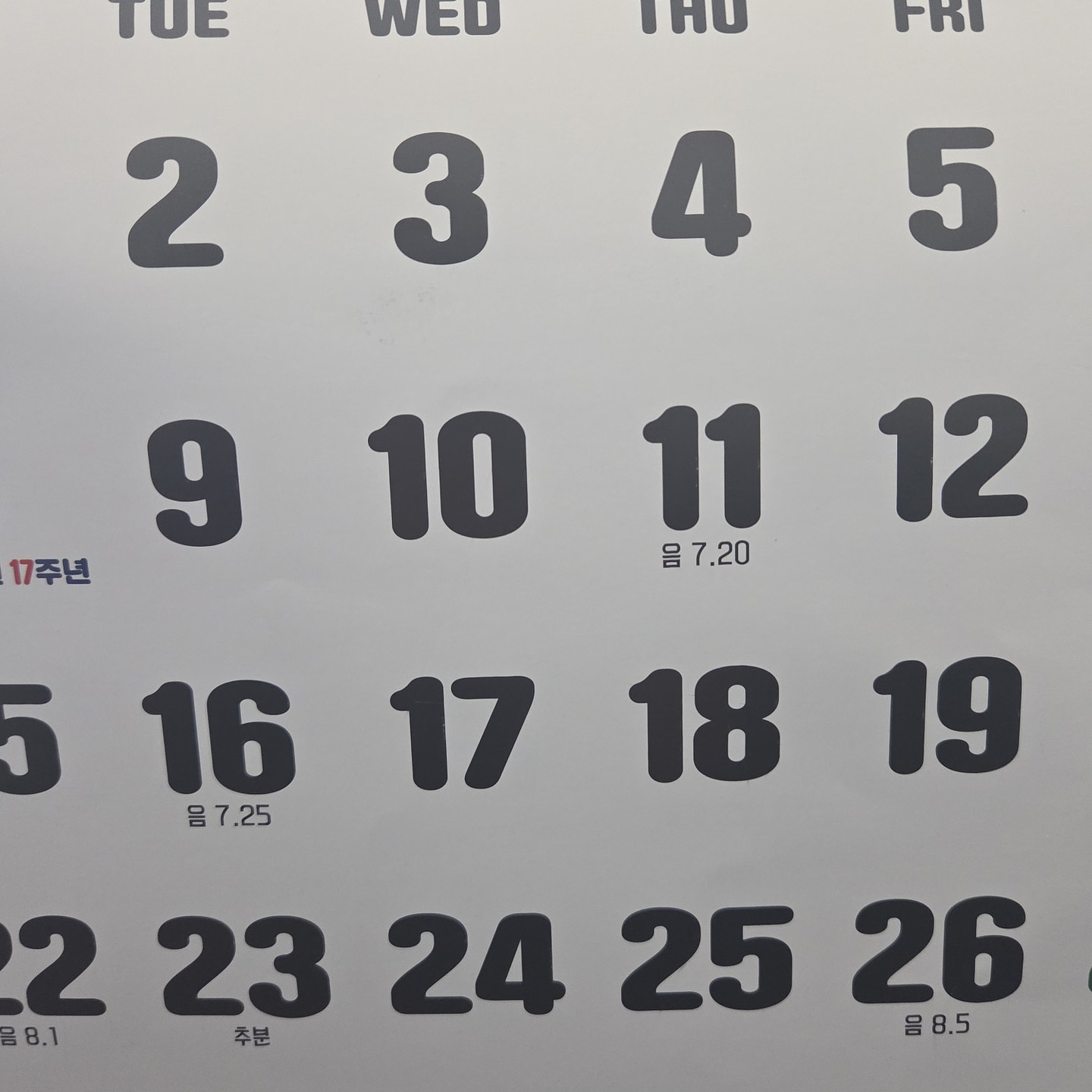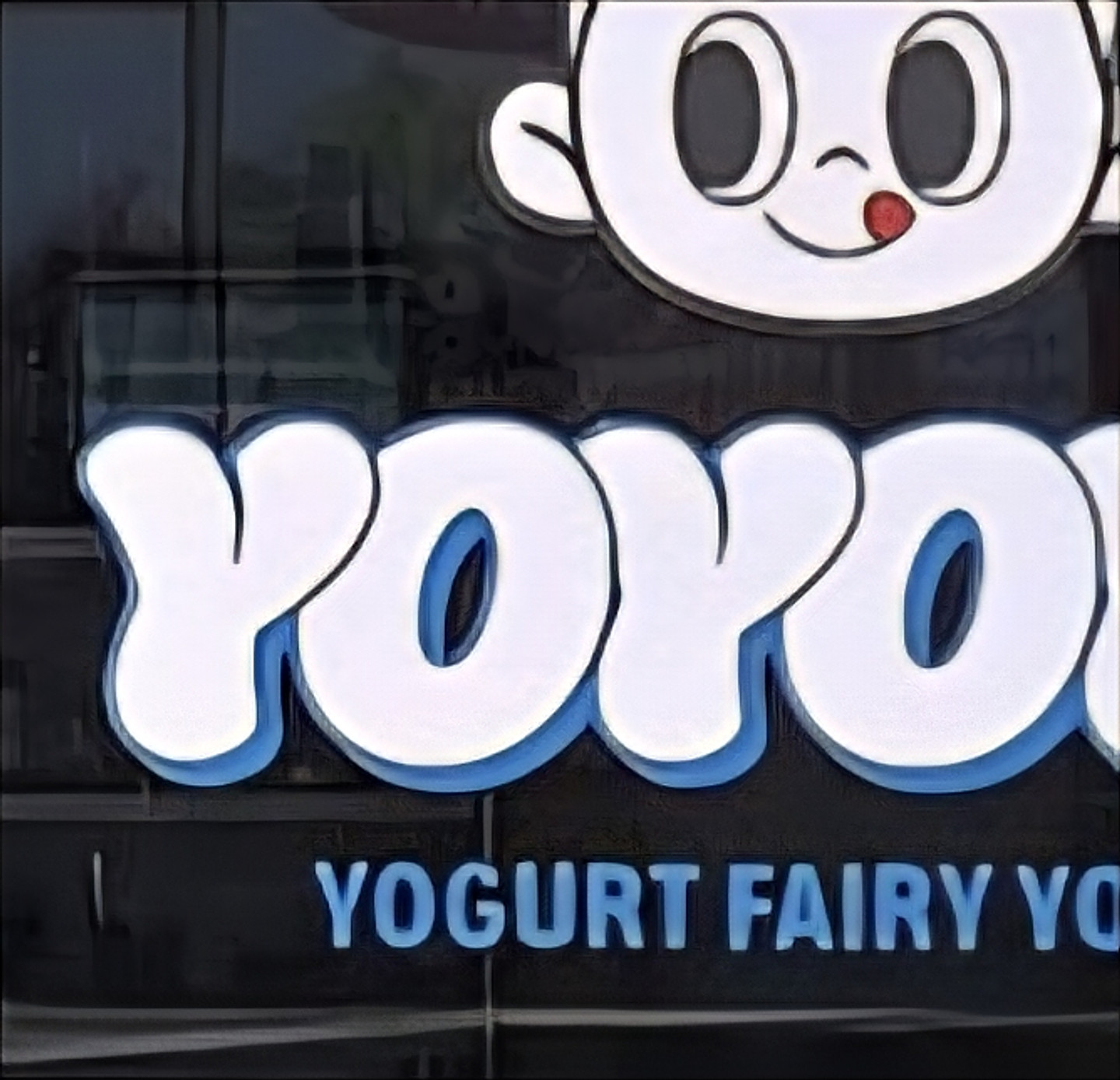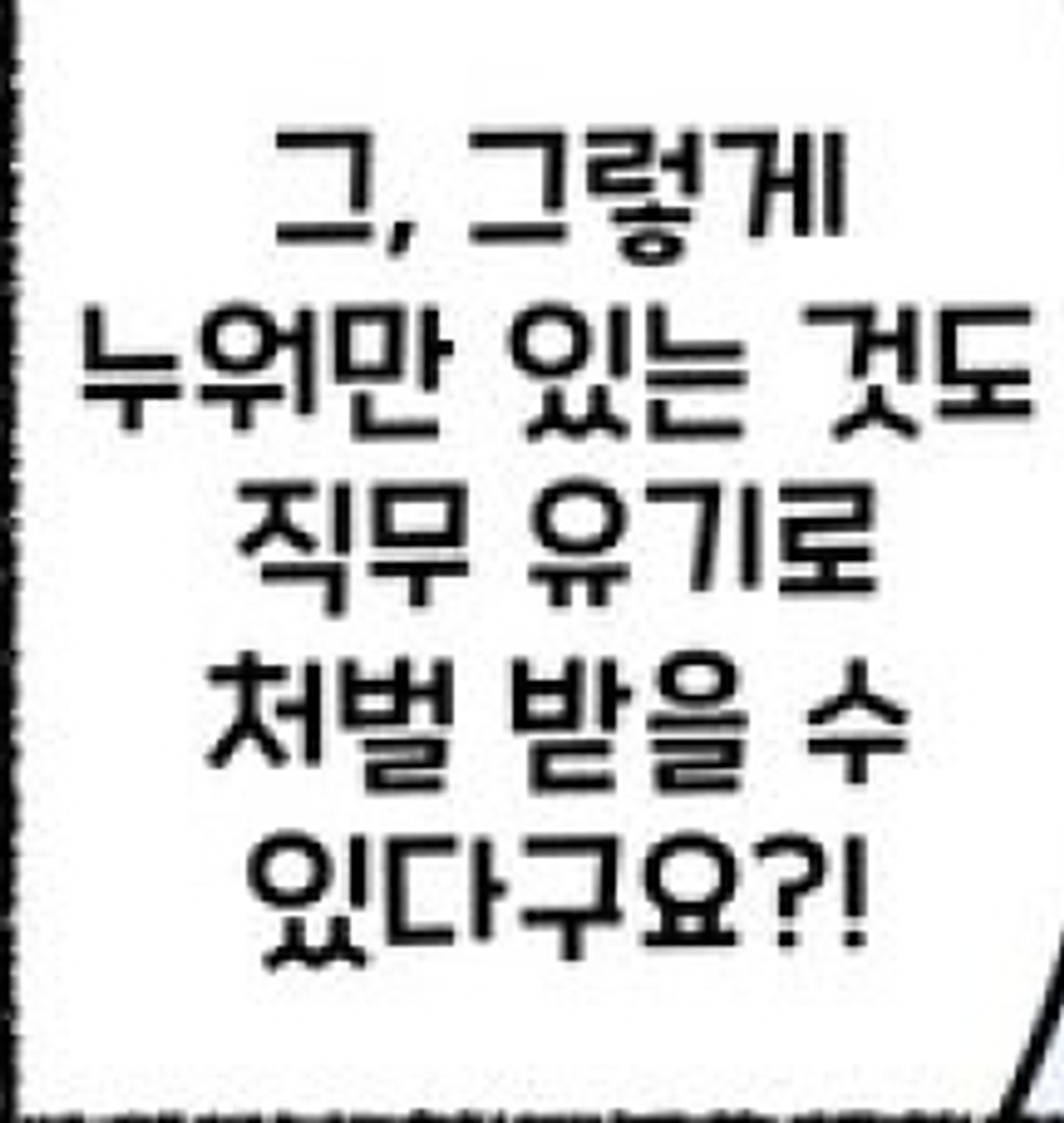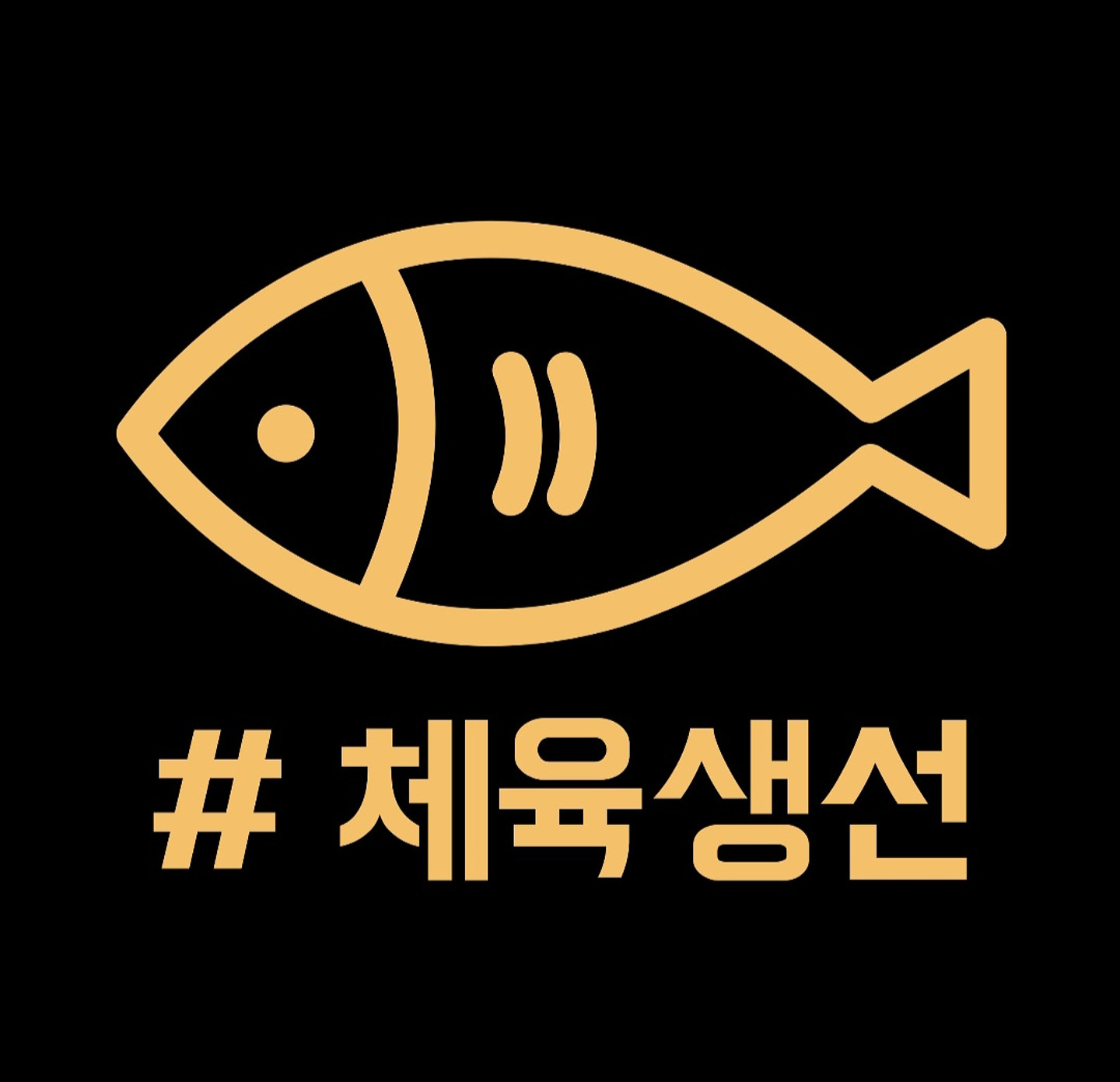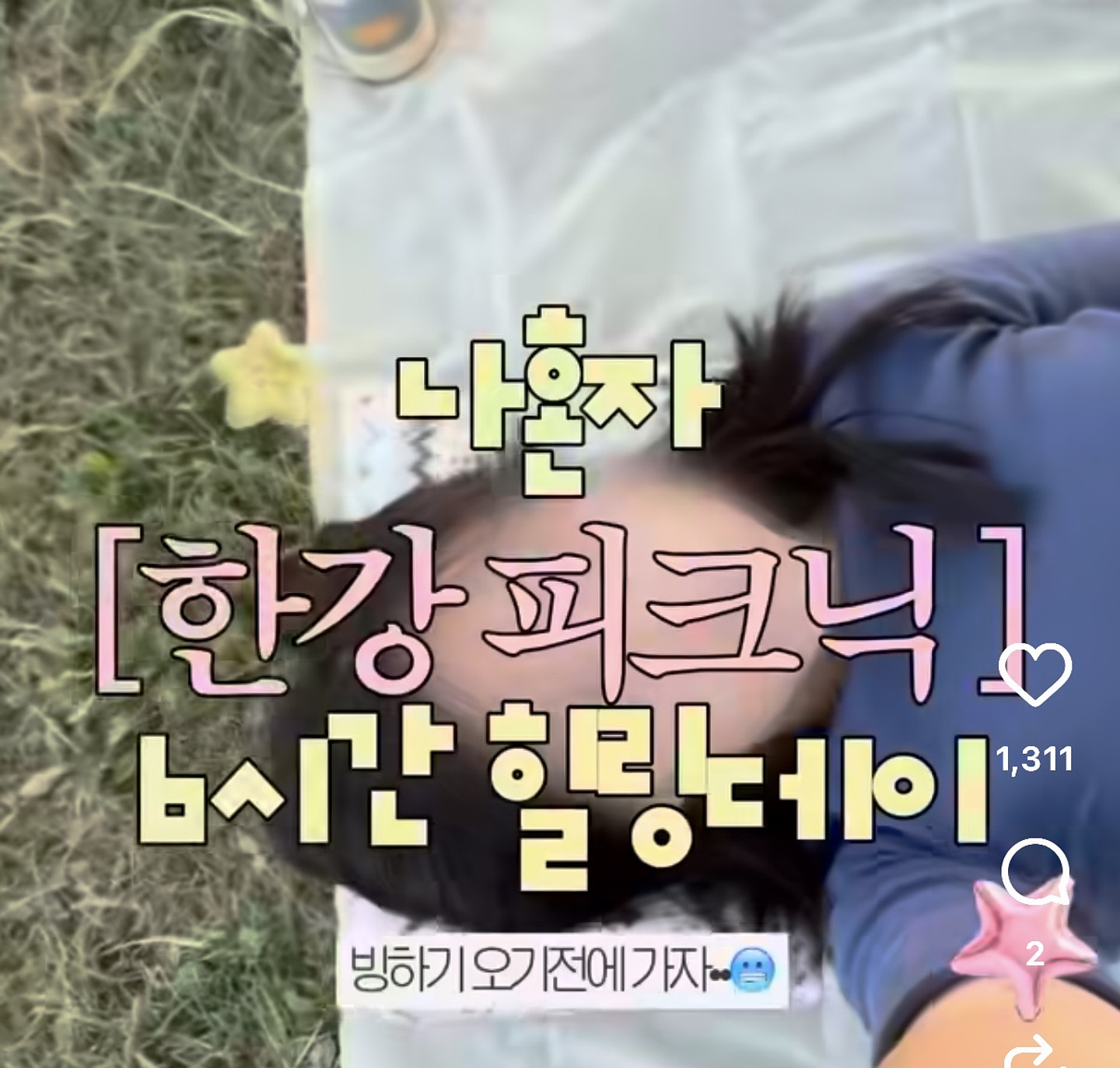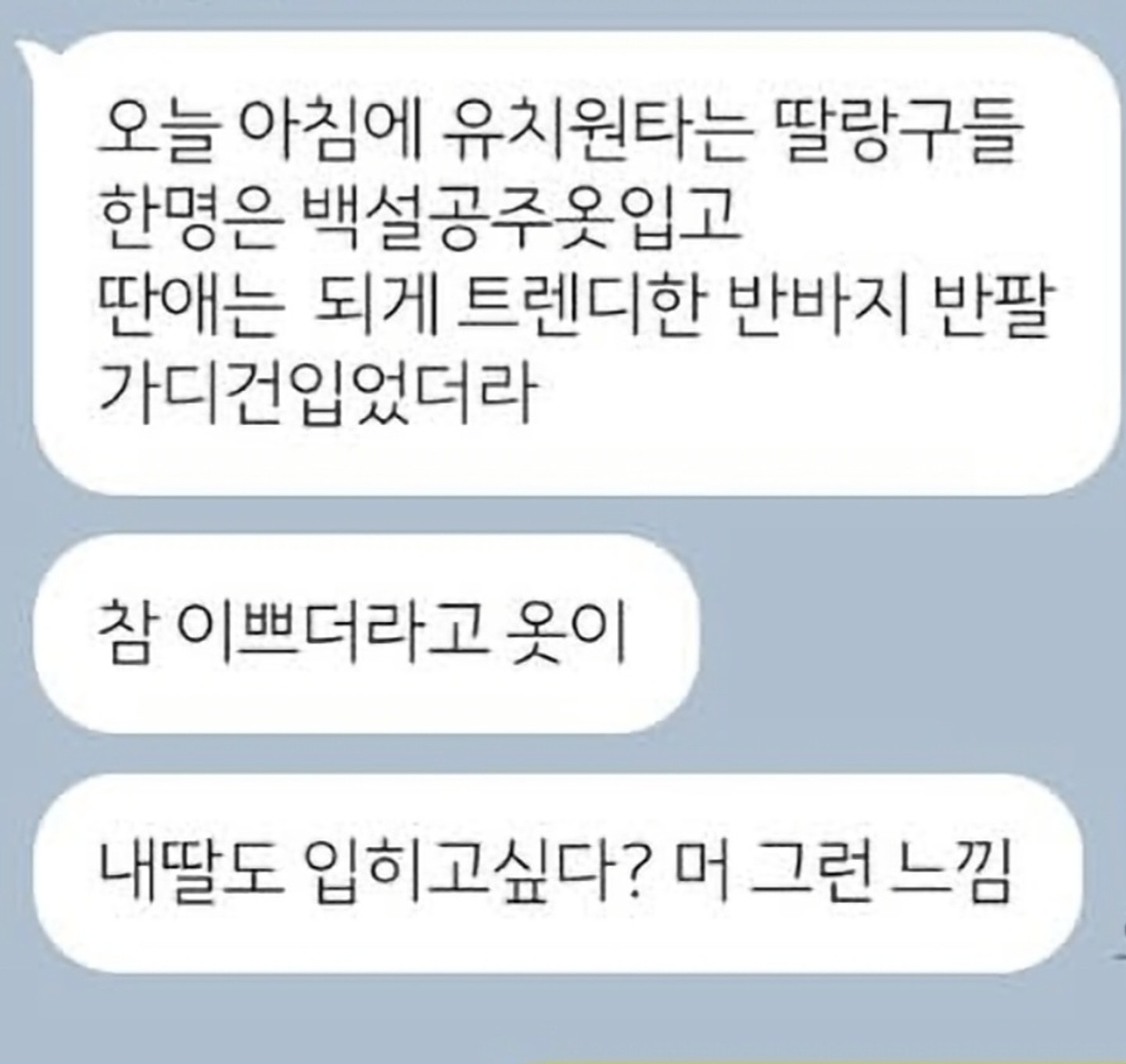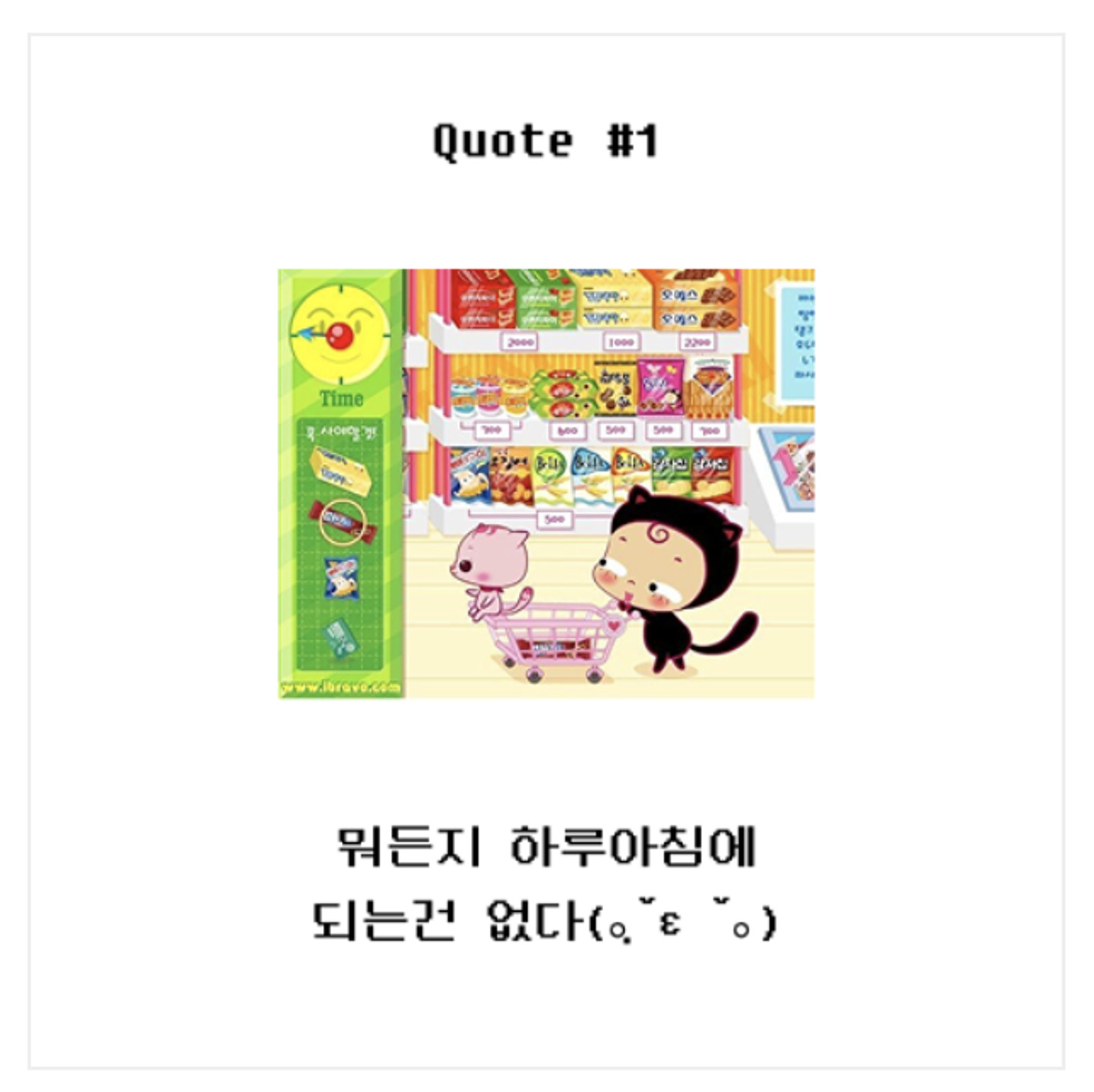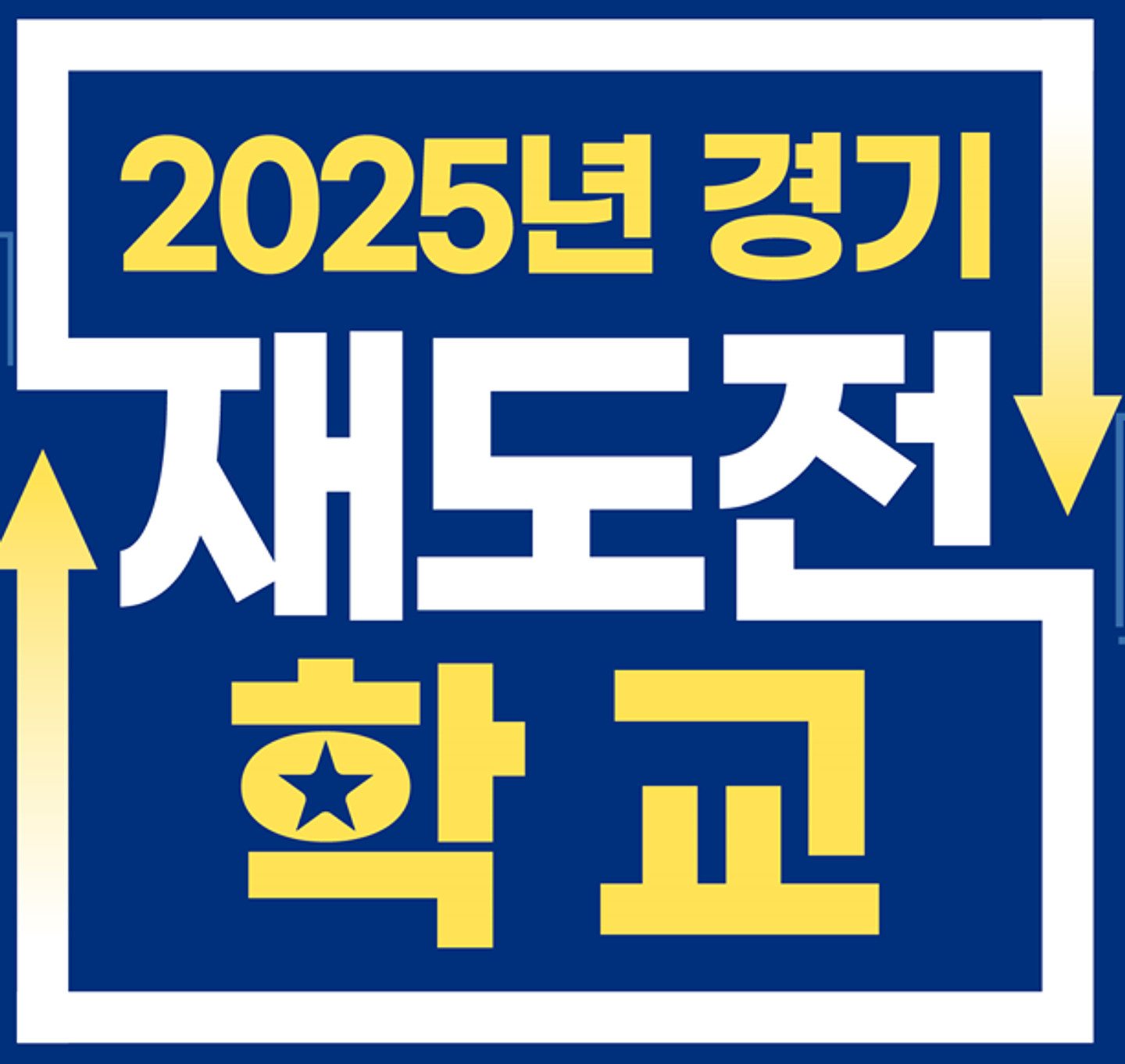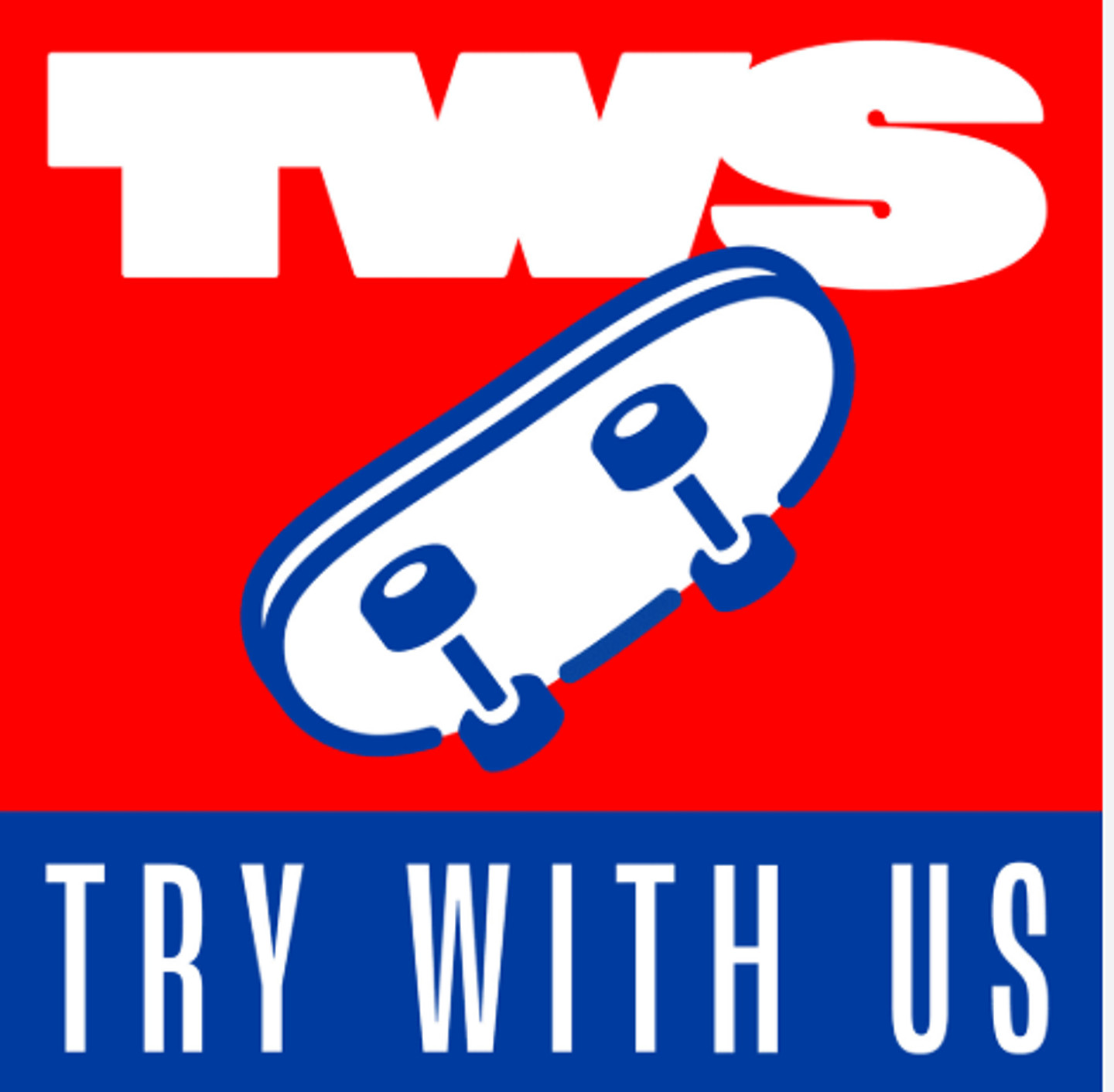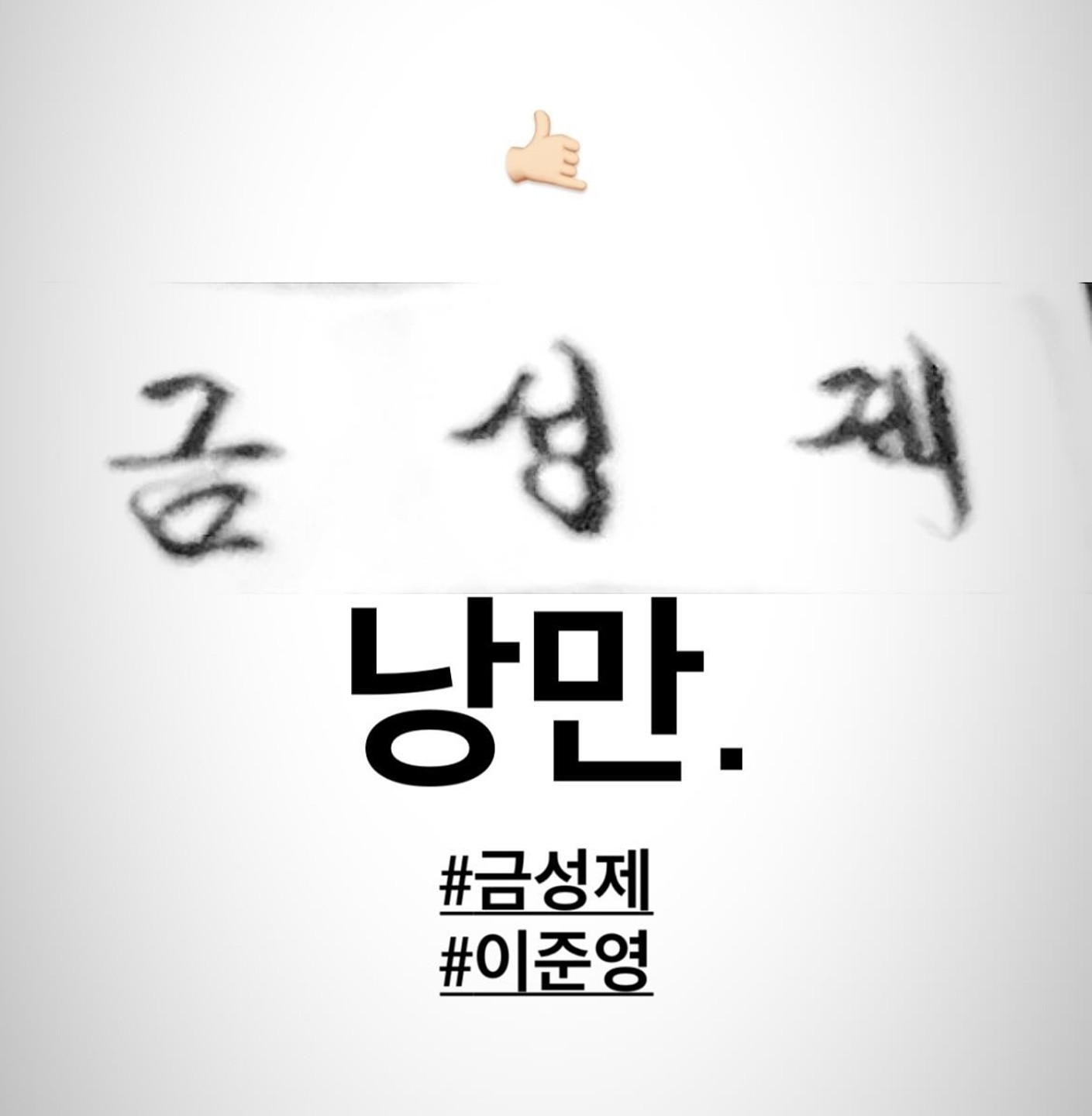
이 폰트 궁금해요!
폰트 궁금합니다!!
한글폰트궁금해영
혹시 해당 폰트 이름 아시는 분 계실까요...? 어디서 본 것 같은데 알 수가 없어 정말 궁금합니다...!!
미리캔버스에서는 고성 금강 누리체 이던데 눈누에서는 고성 금강누리체 하니까 다르더라구요. 눈누에서는 폰트 이름이 뭘까요?
위아래 폰트 모두 궁금해요!
정말 궁금합니다... 무슨 폰트인지.알고 싶어요
폰트 알고싶어요ㅜㅜ
어떤 폰트인지 궁금해오!
이폰트 뭘까요?ㅠㅠ
이거 무슨 폰트일까용ㅜㅜ
이거몰까요
둘다 무슨폰트일까요? 손글씨인가..?
AI가 만들어준건데,,, 수정해야돼서...폰트를 찾아야해요...도와주세요....
이 폰트에 대햐서만 자세히 알려줄수 있을가요?????????
요거 폰트 몰까요 ?? ㅜ
요거 무슨 폰트 일까용??
화질이 좀 안 좋지만.. 폰트 이름 궁금합니다ㅠ
살짝 부드러운 글씨체
비슷한 무료 폰트는 뭘까요? ㅠ.ㅠ
내일까지 찾아야해요... 도와주세요...
주문제작 브이로그 적혀있는 젤 위에꺼랑 중간에 어디까지 찍힐까? 두개 다 궁금해요
이 제목 폰트 뭔지 아시나요?
야구영왕에서 나온 자막인데 무슨폰트일가요?
사진 속 폰트 두가지, 이름이 뭔가요?
이거 아는 분 ㅠㅜㅠ
이거 아는 사람 ㅜ
강민경님 유튜브인데 뭘까요?
산청군< 부분 무슨글씨체인가요 ?ㅠㅠ
무슨 폰트인가요?!
이거 폰트 알려주세요 ㅠㅜㅠ
이미지 속 '코오롱 씨클라우드 기록소' 폰트가 무슨 폰트일까요?
손마킹 비하인드 라고 적힌 폰트 무슨 폰트일까요?
폰트 궁금 ㅜ
미세하게 둥근 고딕체?
이건 혹시 무슨 폰트일까요?
한글에서 작업함
캡컷 전용 서체라고 들었는데 서체 이름아실까요?
이 폰트가 눈에 잘 보여서 궁금합니다! 검은 고딕인줄 알았는데 아니네요 ㅜㅜ
여기 쓰인 폰트 어떤건지 알 수 있을까요
책이나 시집에서 주로 보는 폰트인데 너무 궁금해요!! 혹시 바탕체 일까요,,,?
이 폰트 뭘까요...? 진짜오래된 폰트같은데 꼭필요하네요 ㅠㅠ 고수님들 도와주세효!
폰트가 뭘까요?
무슨 폰트일가요
이거 제 폰 갤럭시인데요 이거 폰트가 뭘까요?ㅠㅠ
이 사진에서 한글, 영문 폰트가 어떤 걸까요? 전문가님들의 도움 필요합니다!!
어떤 폰트가 사용된 건지 아시는 분 계신가요?
두 개 다 궁금해요!!
이 폰트에 대해서 알려주세요. ㅇ의 형태가 독특하네요..
이 폰트에 대해서 알려주세요!
폰트 정보 너무너무 궁금합니다,,,
여기에 사용된 폰트 좀 찾아주세요..ㅠㅠ S와 A가 개성이 강해요.
이 영문폰트가 궁금해요!! 미리 감사합니다!
어떤 폰트인지 모르겠습니다ㅠㅠ
유튜버 단하나 다나나 자막 무슨 폰트인가요?
유튜버 해시킴 무슨 폰트인가요?
무슨 폰트인가요 ㅜ